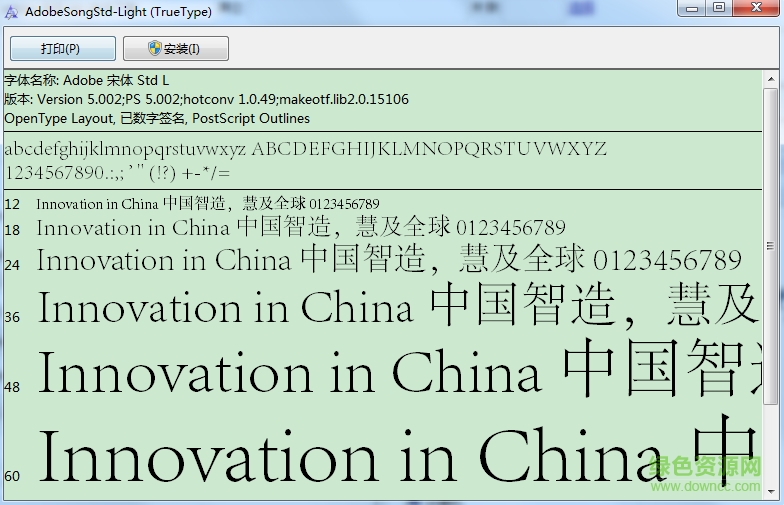
adobe 宋體 std l-亮體
adobe 宋體 std l字體介紹
adobe 宋體 std l是一款專為用于藝術(shù)設(shè)計(jì)方面的字體用于藝術(shù)品裝飾設(shè)計(jì),造型設(shè)計(jì)等字體史依弘的一種設(shè)計(jì)字體軟件,筆劃流暢,字型優(yōu)美,印刷效果好,適于報(bào)刊、雜志的正文。
這款adobe字體非常有特色,非常實(shí)用